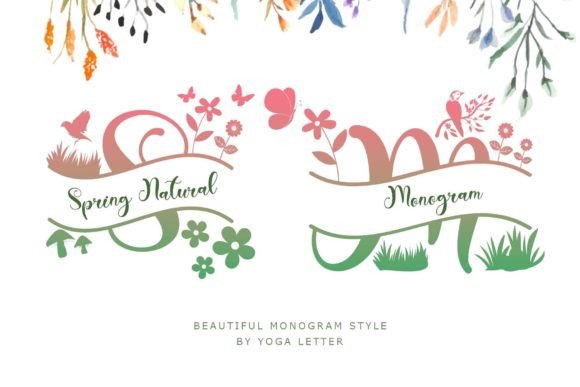
Spring Natural Monogram
Die richtigen Designelemente zu finden, kann eine Herausforderung sein, aber Spring Natural Monogram bietet eine außergewöhnliche Sammlung, die Ihre Arbeit sofort aufwertet.
Mit Präzision gefertigt, bietet Spring Natural Monogram saubere Vektoren, eine reibungslose Typografie und eine kommerzielle Lizenz für ein beruhigendes Gefühl.
Egal, ob Sie POD-Produkte (Print on Demand), Hochzeitseinladungen oder Social-Media-Grafiken erstellen, Spring Natural Monogram ist die ideale Wahl.